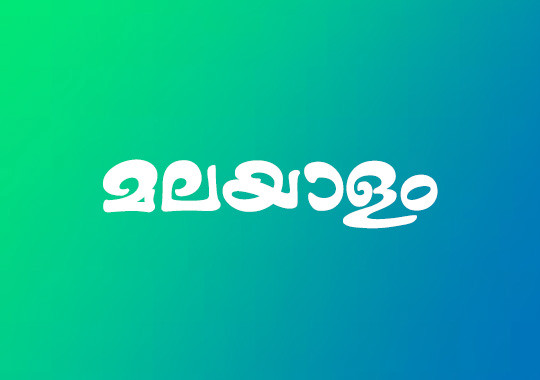
NaseemaB Heavy | Bold Malayalam Display Font
ഡിസൈനുകളിൽ അക്ഷരങ്ങൾക്ക് നല്ല കനവും (Weight) വ്യക്തതയും നൽകാൻ ആഗ്രഹിക്കുന്നവർക്ക് വേണ്ടിയുള്ളതാണ് ML-KV-NaseemaB Heavy. ഇതിന്റെ ബോൾഡ് ലുക്ക് പോസ്റ്ററുകൾക്കും തലക്കെട്ടുകൾക്കും സിനിമ ടൈറ്റിലുകൾക്കും ഒരുപോലെ അനുയോജ്യമാണ്. ദൂരെ നിന്ന് നോക്കിയാൽ പോലും അക്ഷരങ്ങൾ പെട്ടെന്ന് ശ്രദ്ധിക്കപ്പെടും എന്നതാണ് ഇതിന്റെ പ്രത്യേകത.